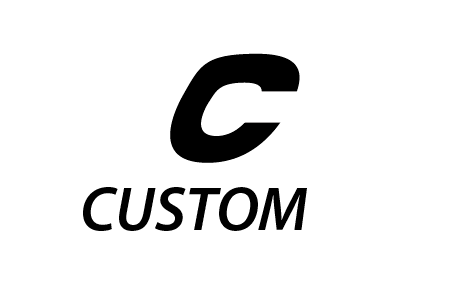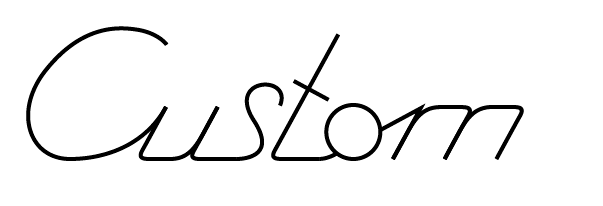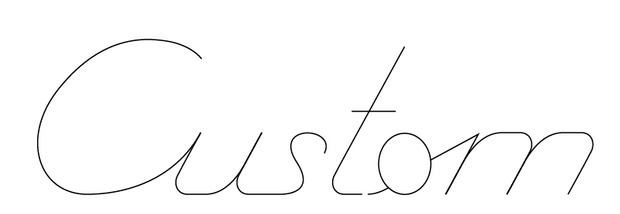
ich bastele an einem Logo. Ich zeige es hier nicht ganz. :schonklar:
C als Bildmarke.
Name in gleicher Schrift enthebt die Bildmarke.
Euere Meinung ist gefragt. Kursive Schrift? Im gleichen Winkel wie das C?
Ich zeige es hier nicht ganz. :schonklar:
Wie bitte? :-?
Name in gleicher Schrift enthebt die Bildmarke.
Bitte? :-?
Übrigens ist das C auf dem Bild irgendwie kaputt oder verformt :-D
Hatte in der Art des C's eine Schrift gebaut. hat überhaupt nicht gepasst.
Was findest das kaputt aus sieht?
ist auch nicht der ganze Teil des Logos...
bin der Meinung das beide Elemente unbedingt den gleichen Neigungswinkel benötigen.
Was findest das kaputt aus sieht?
Na ja, das »c« sieht ziemlich verbogen aus. Das ist aber vermutlich Absicht …!? :-?
Verrätst Du uns, für welche Branche das Logo gedacht ist, wenn Du schon nicht das ganze Logo zeigen willst?
Das »C« sieht aus wie mit ner Walze überfahren ... schaut für mich unmotiviert aus.
… Ich zeige es hier nicht ganz. …
Wie sollen wir dann etwas dazu sagen?
Euere Meinung ist gefragt. Kursive Schrift? Im gleichen Winkel wie das C?
In einem Logo sollten Neigungen und Schrägen immer im gleichen Winkel stehen oder sich klar und deutlich unterscheiden, wenn es denn für die Aussage notwendig ist, dass es verschiedene Winkel gibt.
War das in etwa die Frage?
dazu kommt die Frage: In welchem Winkel des C?
Das meinte ich mit »unmotiviert«. Es schaut aus wie ein ausgerollter Plätzchenteig, in verschiedene Richtungen verzerrt.
wahrlich very custom.
wie kathrin bereits bermerkt hat: ohne einen kleinen hinweis über die intention und die verwendung des/eines logos wirst du hier über das formale nicht besonders weit kommen.
das sich die konzeption und gestaltung eines logos aber keinesfalls von dem heraus ergeben soll und es auch nicht unter diesem gesichtspunkt gewertet werden kann, versteht sich glaub ich von selbst. (das ist im übrigen auch der grund, warum all die »logo«-bücher nicht wirklich als inspiration funktionieren, da sie über die präsentation eines signets oder einer type als »strukturelles ornament« nicht hinausgehen.
rein formal sehe ich dahinter keinen sonderlichen anspruch bzw irgendeine art von kommunikativen faktor. der bereits gefallene begriff »unmotivert« trifft es da meiner meinung nach sehr passend. ich würde mir noch anmassen »austauschbar« zu verwenden.
geh vielleicht noch einmal in dich und überleg dir was die form für den inhalt des projektes ausdrücken soll. bring es zu papier und zeig es, ich bin sicher dann wirst du fundiertere und für dich zielführendere auskünfte erhalten.
sorry. Habe erst jetzt reingeschaut. Das mit dem nicht ganz zeigen ist nicht böse gemeint. Ist hier echt mein Lieblingsforum. Nur schlechte Erfahrungen gemacht.
Das C ist so 'unmotiviert', Kunde will Restaurant eröffnen aber mit dem Background von 60er /70er Jahren Autos. C ist hat hinten noch Flammen und sollte an die Comicdarstellung eines drehenden Reifens anlehnen.
Bin davon aber jetzt weg. Aber die Antwort wollte ich haben.... gleicher Winkel oder deutlich unterscheiden.
Versuche jetzt erst die Schrift, in Anlehnung an Kofferraumbeschriftung zu gestalten. *noch nicht fertig*
Stosse da aber auf ein anderes Problem. Mache das in Illu mit Pfaden. Also Pfadlinie in der Mitte der Linie.
Gibt es eine Möglichkeit einen umrandenden Pfad zu erzeugen? Oder bleibt mit nur die Sache von Hand noch einmal zu umfahren
Kritik an der Schrift willkommen... :tuschel:
ganz ehrlich: Lass das jemand machen, der was davon versteht. Dein gerade gezeigter Entwurf geht noch nicht mal als verwackelte Handskizze durch, das ist einfach nur grauenhaft.
Zu deinem Illustrator-Problem findet sich im Vektorgarten eine Lösung, runterscrollen bis "Objekte mit einer gemeinsamen Kontur versehen".
… Aber die Antwort wollte ich haben.... gleicher Winkel oder deutlich unterscheiden. …
Solange du verschiedene Schrägen in deinem C verwendest, ist es egal, es wird nie wirklich stimmen.
Oder nimm einen bestehenden Font …
gibt’s beim Eichhörnchen
verwackelt??
das s zu hoch, der t-Strich schräg, das o kreisrund, der Anschluss o–m passt nicht …
okay. wenn das alles ganz bewusst passiert?? wenn es so meinem optischem Empfinden entspricht?
Ich mach ja keine Schrift für einen Fliesstext.
aber immerhin konntest du dich zu einer konstruktiven Kritik durchringen. Ich danke abermals.
dann werde ich wohl all die Zeit für schlecht Grafik bezahlt.
Da wärst Du ganz sicher nicht der erste und nicht der letzte ... ;-) Spaß beiseite, Bertels Kritik war in ihrer Deutlichkeit etwas harsch, aber wenigstens ehrlich :-) Die Schrift von Dir sieht einfach nicht nach dem aus, nach was es (laut Dir) aussehen soll, und auch einfach nicht nach guter Schrift: da würde ich wirklich zu einem Font greifen. Du kannst ihn ja noch leicht individualisieren oder mit einer schönen, passenden Bildmarke einzigartiger machen. Nicht böse gemeint, wirklich nicht :-D